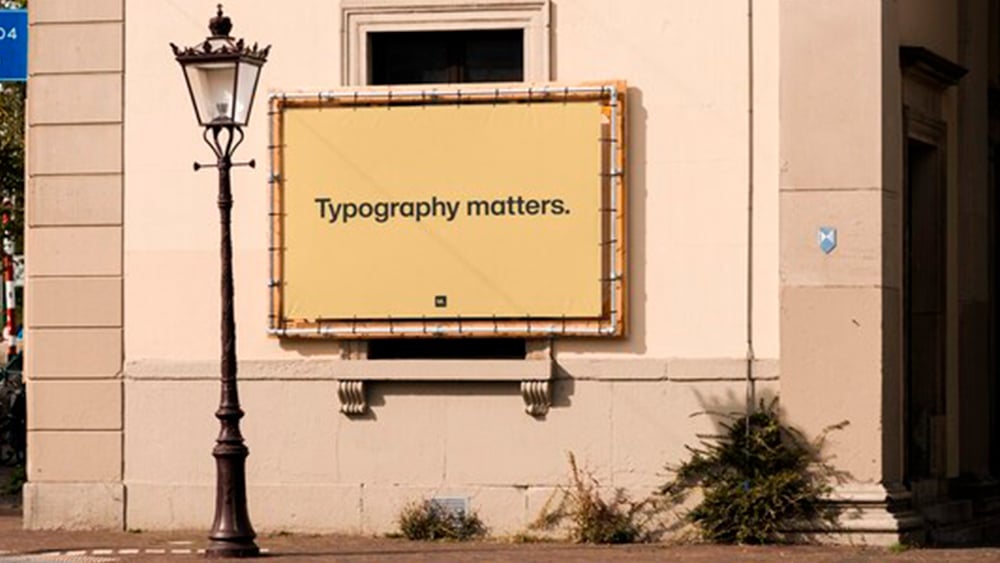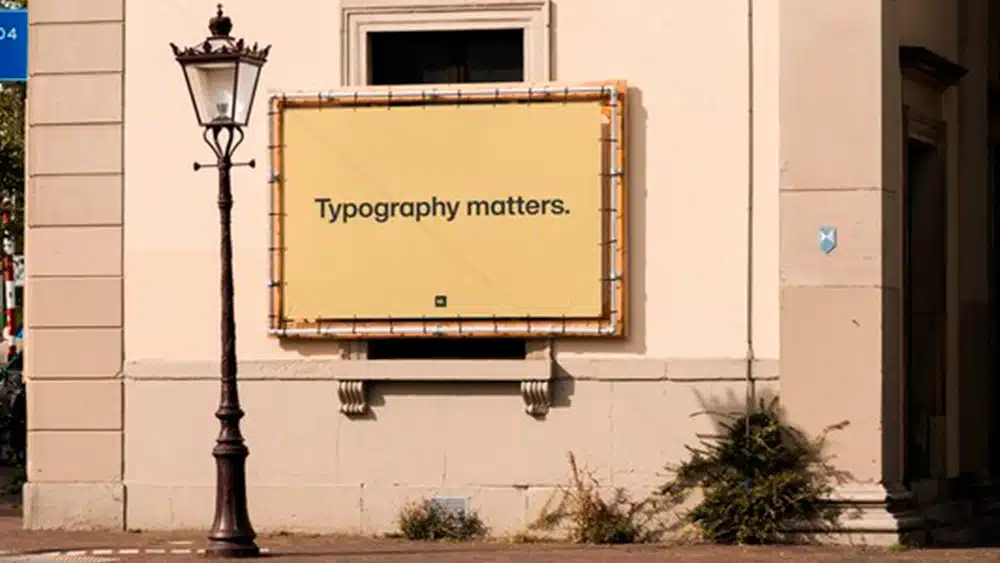
Ново проучване разкрива как шрифтовете карат хората да се чувстват в различните части на света
Оказва се, че шрифтовете имат различни асоциации в различните страни...
Изборът на подходящ шрифт е важен, понеже той може да предава различни емоции. Това може да окаже огромно влияние върху начина, по който се възприема даден проект или марка, но ново изследване показва, че емоциите, които различните шрифтове предават, могат да се различават в различните части на света.
Компанията за цифрово набиране на шрифтове Monotype е използвала неврологията, за да проучи как различните стилове шрифтове предизвикват различни емоционални реакции в зависимост от държавата. Компанията е анкетирала хора в 8 държави, за да види как те оценяват различните шрифтове за определени асоциации.
Проучването на Monotype, озаглавено Typography Matters: Как да се възползваме от неврологията, за да изградим запомнящ се бранд е фокусирано върху Австралия, Франция, Германия, Япония, Португалия, Испания, Обединеното кралство и САЩ. Някои от тези страни може да изглеждат сравнително близки по отношение на културата, но предпочитанията и емоциите, свързани с различните шрифтове са различни.
Бяха направени някои общи изводи. Беше установено, че серифните шрифтове като Cotford предават честност и качество, докато безсерифни шрифтове като FS Jack предават иновация и различие, а геометричните безсерифни шрифтове като Gilroy Bold се свързват с честност и яснота.
Серифните шрифтове имат серифи. Серифът е малка завършваща линия в края на гредата на буквения знак.
Безсерифните шрифтове нямат серифи, логично. Безсерифните шрифтове са по-лесни и приятни за дигитално четене.
Изследването обаче установи, че респондентите от англоговорящите страни (Австралия, Обединеното кралство и САЩ) показват предпочитание към отличителните характеристики на шрифтовете. Франция, Португалия и Испания показаха значително предпочитание към „класическия серифен стил на Cotford“.
Докато FS Jack Regular получи най-висока оценка за предаване на доверие в седем от осемте държави, Cotford се представи най-добре в Германия. Установено бе, че готическите, нискоконтрастни шрифтове се справят много добре с предаването на иновативност в Япония, където висококонтрастните шрифтове, които запазват традиционното усещане се смятат за заслужаващи доверие.
Изследването е проведено в сътрудничество с компанията за приложни невронауки Neurons. Данните са събрани чрез анкетиране на 1957 участници. В страните, използващи латински шрифтове са тествани шрифтовете FS Jack, Gilroy и Cotford. В Япония тестваните шрифтове бяха DNP Shuei Mincho, Shorai Sans и Tazugane Gothic.
В проучването са използвани 3 вида стимули: отделни думи, изречения, в които са използвани тези думи, и изречения, включващи имитация на марка. Респондентите оцениха тези комбинации, като взеха предвид редица емоционални показатели: искреност, запомняне, надеждност и доверие.
Докладът предоставя интересни идеи за маркетолози, творци и публични органи, разработващи информационни кампании, като потвърждава, че идеалният избор в една страна няма непременно да е най-добрият в друга. Това е особено полезно да се има предвид в светлината на засилващата се тенденция за стартиране на глобални, а не местни кампании.